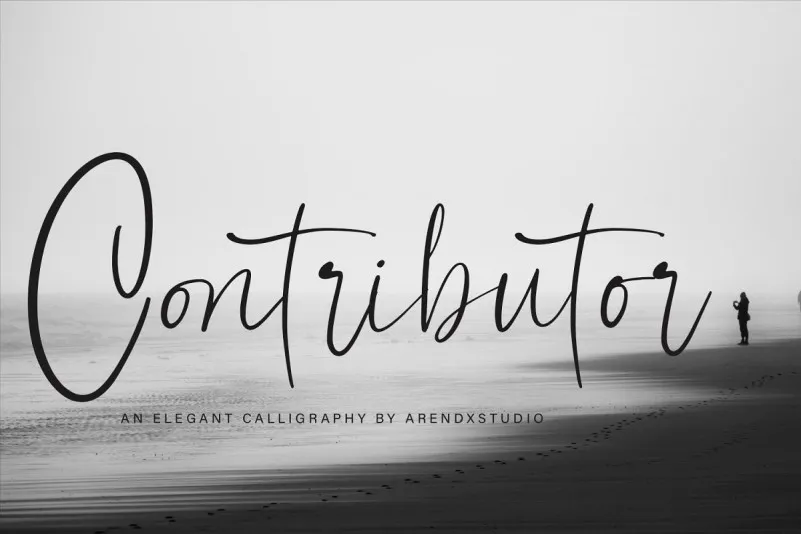
Contributor Calligraphy Font – Download Grátis
Descubra uma nova forma de expressar seu design com a Contributor Calligraphy Font, criada especialmente para escrita elegante e sofisticada. Esta script font é perfeita tanto para personalizar suas marcações individuais quanto para criar um visual único em cartões de convite de casamento ou cards empresariais. O uso do estilo casual e distintivo do Contributor Calligraphy Font tornará seu design ainda mais luxuoso, criando uma identidade visual coesa e sofisticada. Seja para seus anúncios de marca, logos ou até mesmo cartões de visita, esta font se destaca por sua facilidade em transformar textos grandes em elegantes e detalhados nomes de marca. Com uma ampla gama de letras maiusculas e minusculas, caracteres numéricos e ligaduras que atendem aos padrões reais de alta qualidade, a fonte do Contributor é perfeita para quem busca estilos únicos e elegantes em seus projetos.